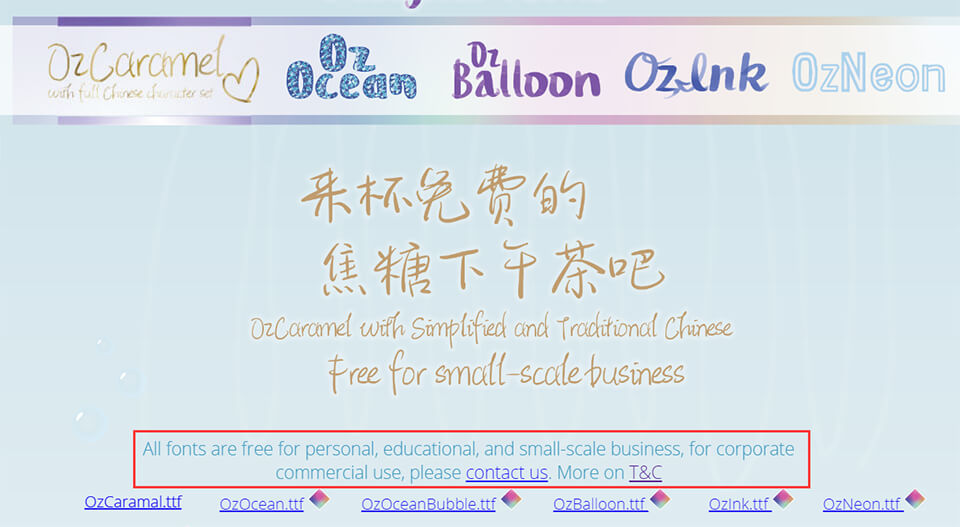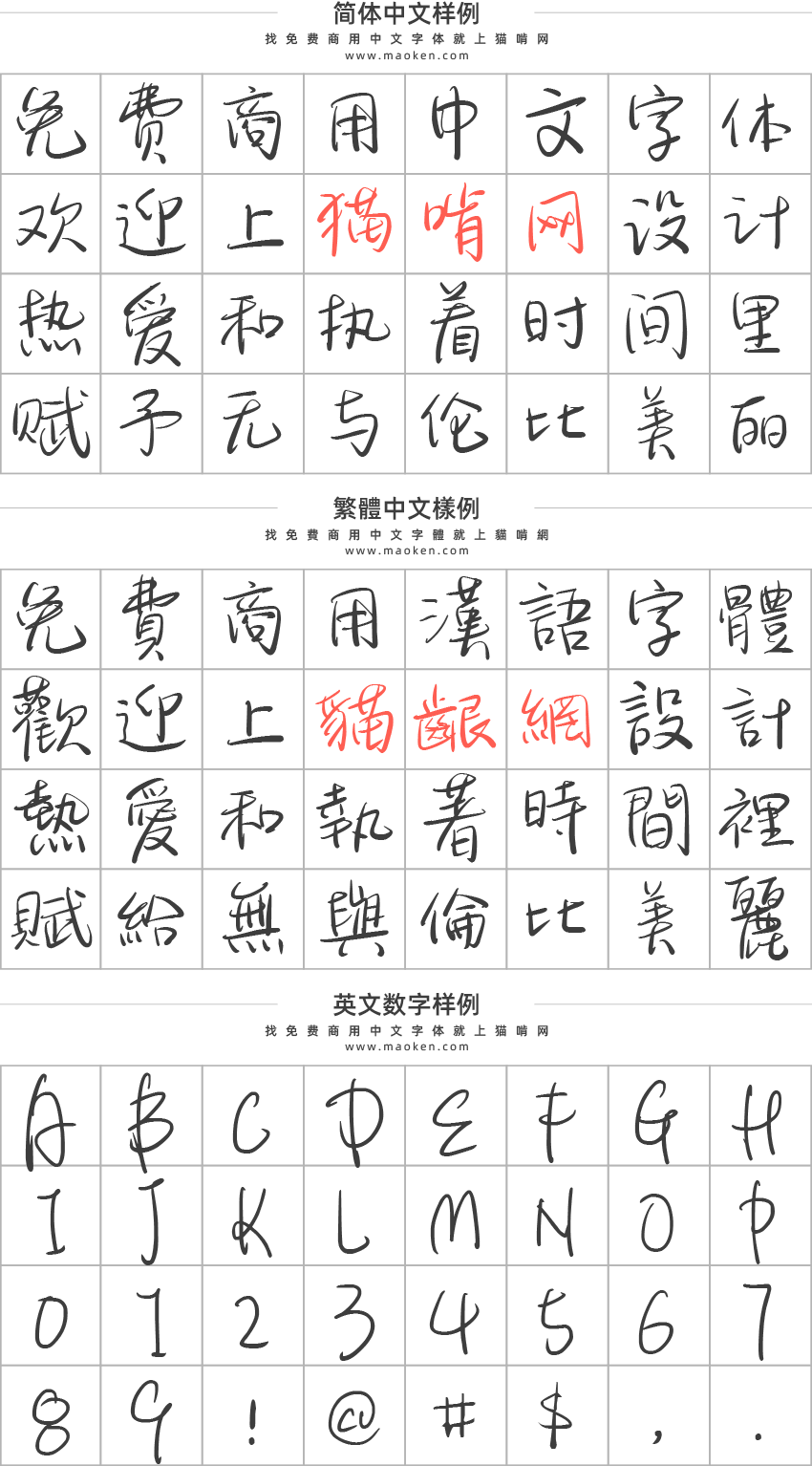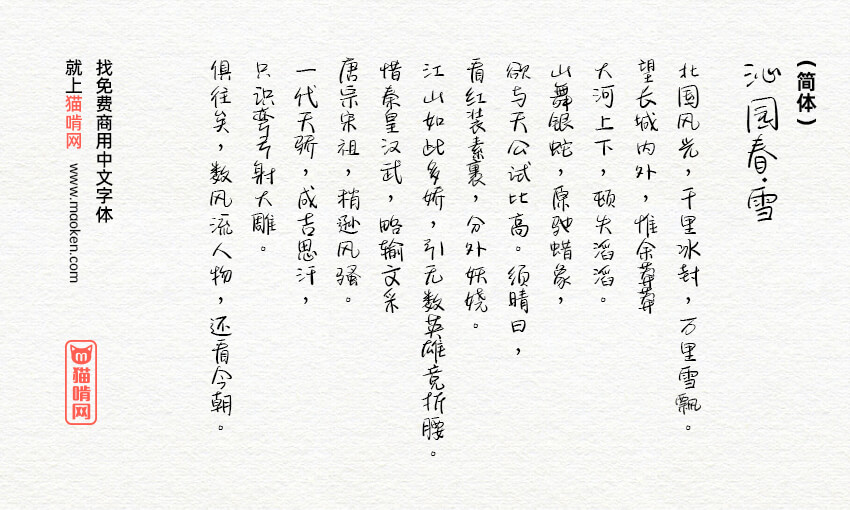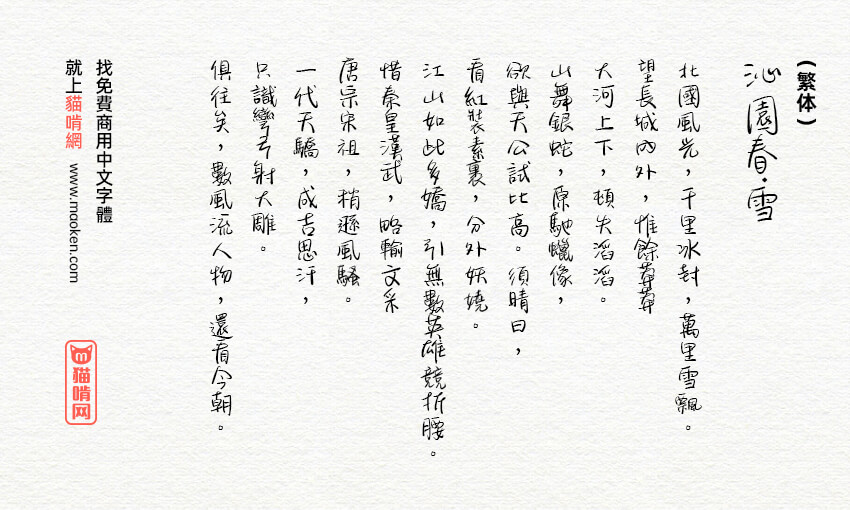
新蒂焦糖体:来杯免费的焦糖下午茶吧 新蒂出品免费商用手写字体
新蒂焦糖体是新蒂字体在2020年推出的一款针对个人和小型企业的免费商用字体。新蒂焦糖体是一款手写字体,其字形活泼可爱,清秀的字体有着灵动的特质,特别适合小清新,小文艺的设计风格。新蒂焦糖体支持超过10000+简体字、繁体字、拉丁字母,可以说是比较齐全了。
和之前的Oz焦糖体下午茶有什么区别?
• 没啥区别,就是换了个名
u1s1,商用这些字体质量也很高,包含的字数都很齐全,我挺中意糖果体蜡笔体哈哈哈哈哈。
和自己初中时班长的字体很像23333
这个字是真的超好看!我的心头好!